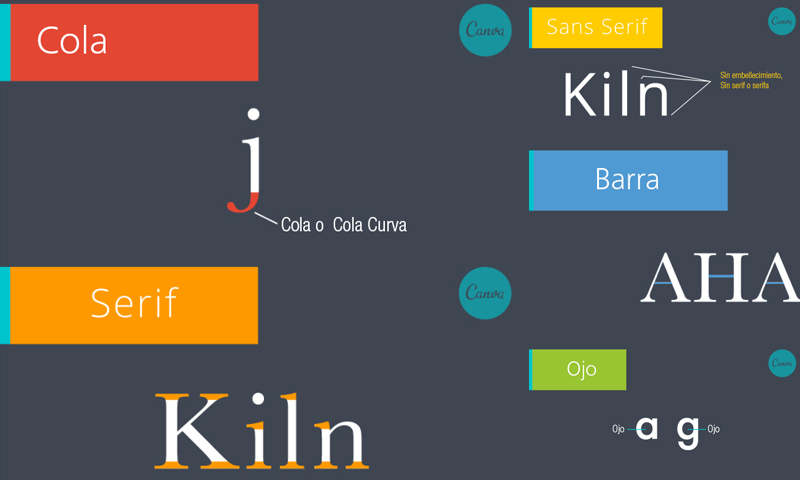
Enterate cuáles son los términos más utilizados a la hora de referirte a una tipografía o bien a algún detalle, gag tipográfico o elemento que forma parte del mundo de las fuentes tipográficas.
En este post encontrarás imágenes con los nombres de cada uno de los términos del vocabulario tipográfico y la explicación como por ejemplo:
- ¿Qué es un serif?
- ¿Qué es un un caracter?
- ¿Cuál es la línea base?
- ¿Qué son las ascenentes?
- ¿Cuál es la altura de la x?